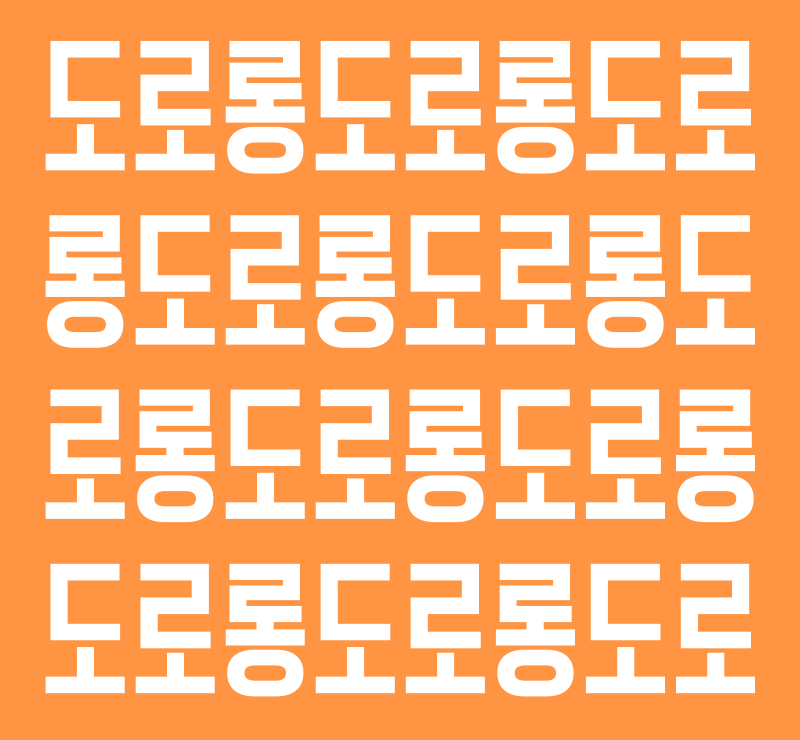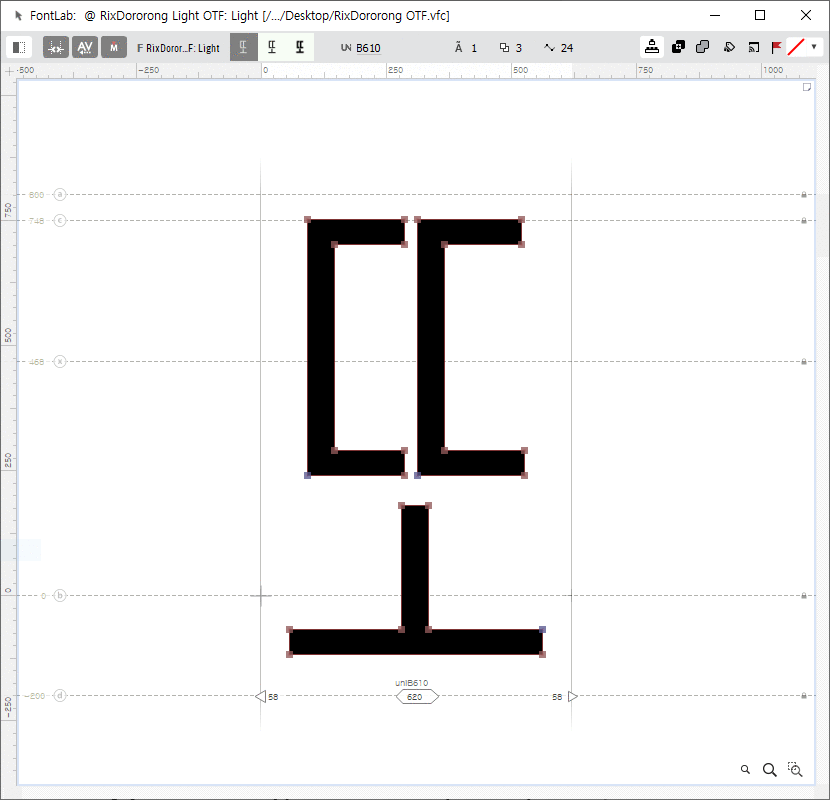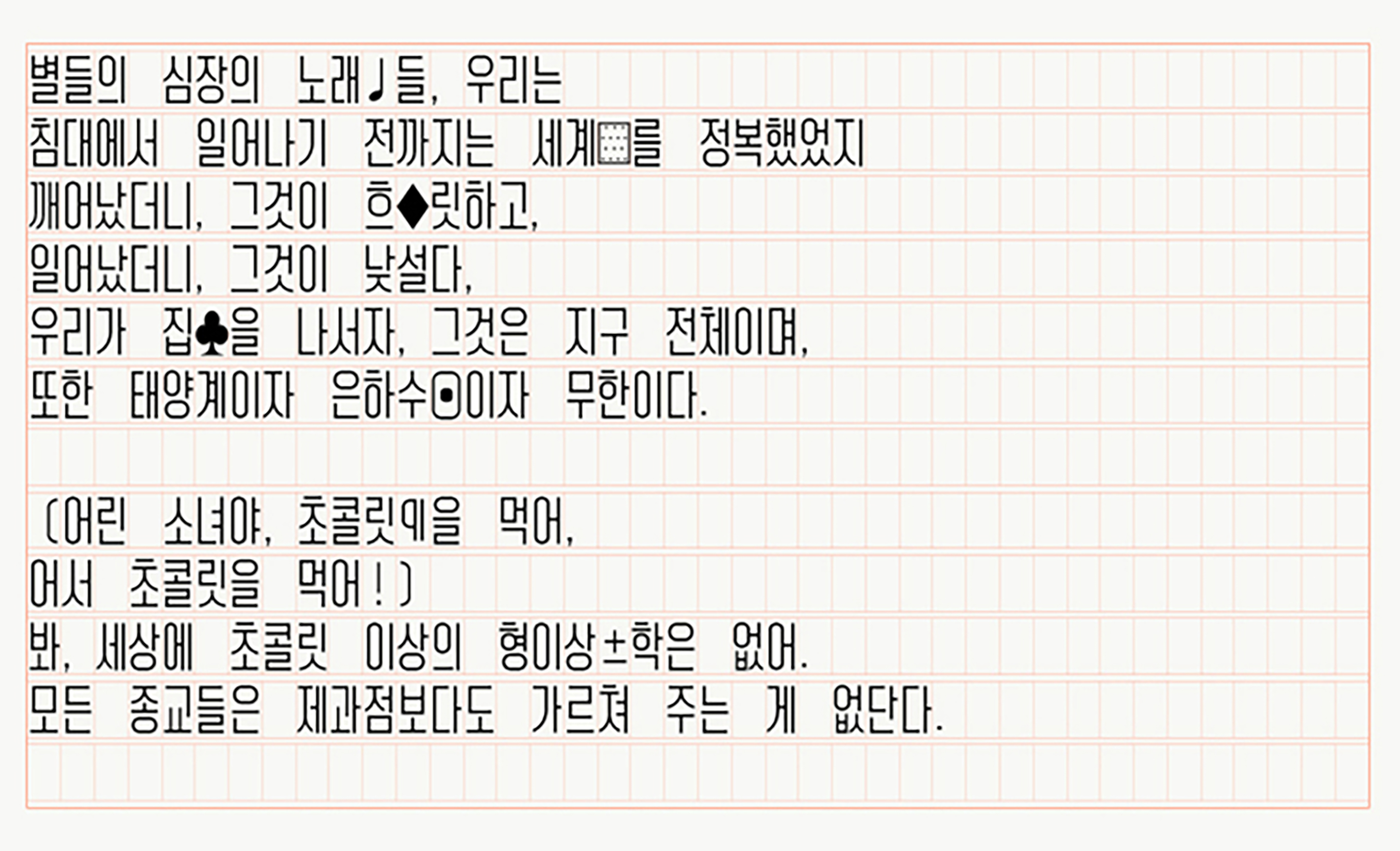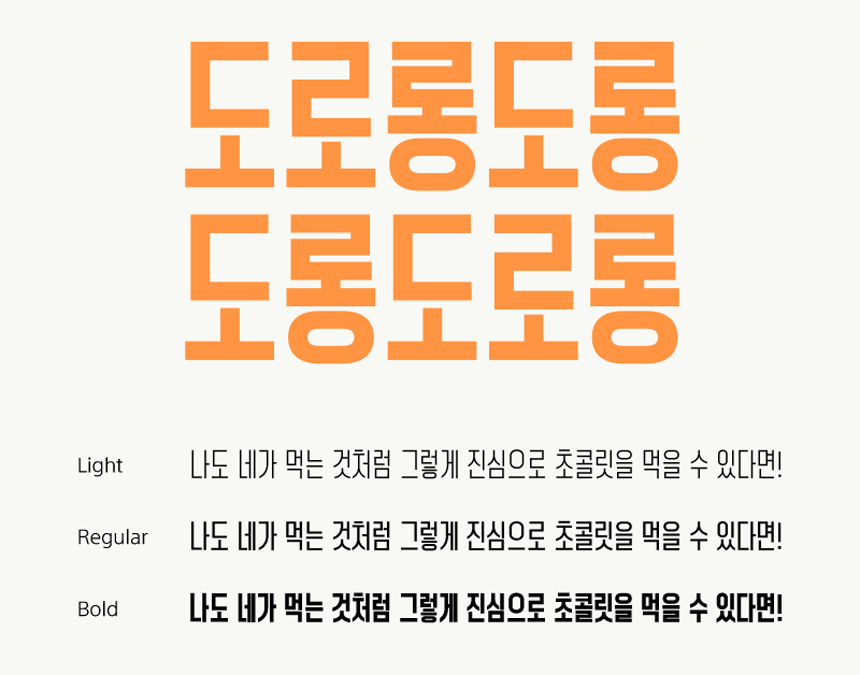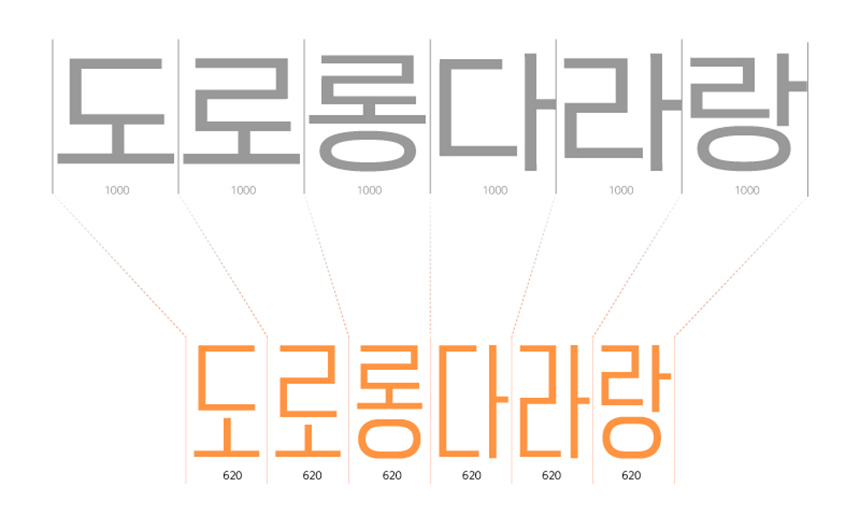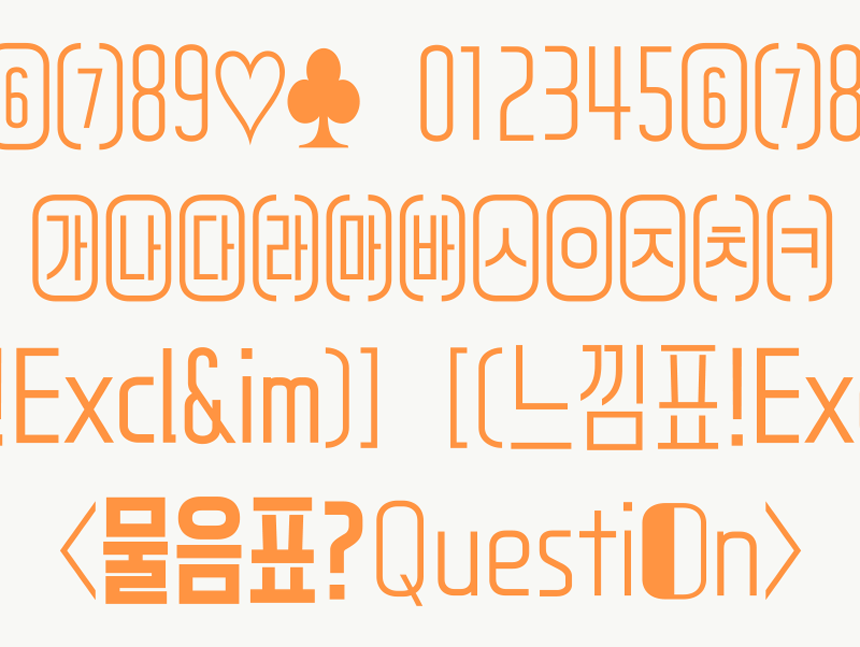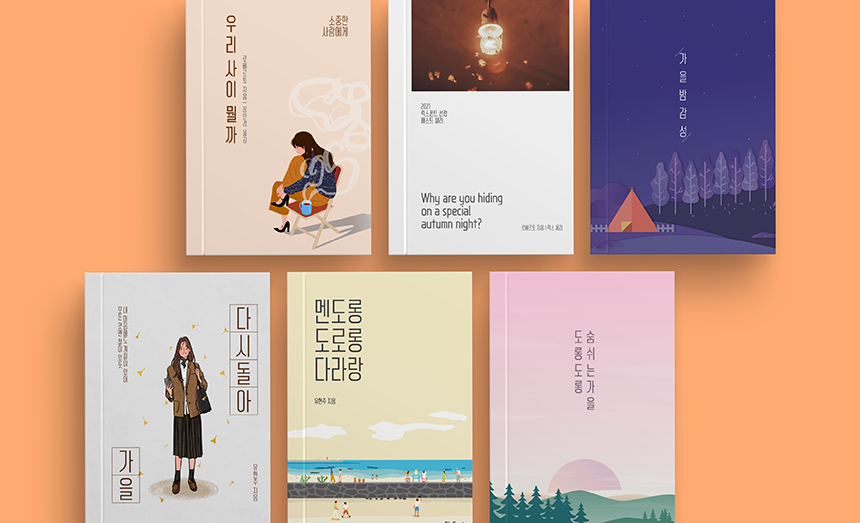
안녕하세요. 오늘은 선선한 가을과 함께 찾아온 시원한 헤드라인 폰트, 10월의 신서체「Rix도로롱」을 소개합니다! 제목용 서체이지만 얇은 거 두꺼운 거 다 되는 활용도 높은 장체 스타일의 글꼴입니다. 폰트에 대해 딥하게 알 수 있는 Rix도로롱 제작자 유현주 디자이너와의 심층 인터뷰! 먼저 함께할게요:)
안녕하세요, 유현주 디자이너님. 10월의 신서체로 처음 인사드리게 되었는데 소개 한번 부탁드릴게요!
안녕하세요. 도로롱으로 데뷔(!)하게 된 글자 만드는 것을 좋아하는 유현주입니다.
이번에 작업하신 'Rix도로롱'은 어떻게 기획하게 되신 건가요?
회사에서 최근 출시하는 폰트들이 정사각에 가까운 네모꼴인 것을 보고 장이 좁은 폰트를 그리게 되었습니다. 폭이 좁고 일정한 격자 모듈을 모티브로 길고 얇은 유리잔에 담긴 모히또가 연상되어 원제는 모히또로 정했었는데, 단어에 여름이 묻어있어서 좀 더 가벼운 느낌이 나는 도로롱으로 이름을 바꾸게 되었습니다. 이름 지어주는 게.. 글자 만드는 것만큼 어렵더라고요(웃음)
제작하면서 가장 어려웠던 부분이 있다면 무엇인지?
아무래도 좁은 자폭을 갖고 있다 보니, 획이 두꺼워지고 많아질수록 일정함을 유지하기가 어려웠어요. 그래도 이번을 기회로 글자를 그리는 다양한 방법과 규칙들을 배울 수 있었습니다:)
'Rix도로롱'의 제작자로서 이 폰트의 가장 큰 매력 포인트를 뽑는다면?
격자무늬요(편-안)ㅎㅎ 제목용으로 제작했지만 한글 자폭이 일정하기 때문에 긴 문장이나 문단을 썼을 때 보이는 격자무늬가 마음에 안정을 가져다줍니다. 직사각 형태에 꽉 찬 골격, 고정폭이 주는 깔끔하고 딱 떨어지는 매력!
디자인 영감이 필요할 때 자주 보는 디자인 플랫폼, 또는 인스피레이션(inspiration)이 있다면?
원래는 책이나 포스터의 레터링을 많이 찾아보고 모았었는데, 요즘은 기성 폰트를 제목에 사용하는 경우가 많더라고요. 그래서 요즈음엔 옛날 LP의 레터링들이나 최근에 출시되는 외국 폰트를 주로 찾아보고 있습니다.
앞으로 또 어떤 폰트를 제작하고 싶으신가요?
최근에 배리어블 폰트에 흥미가 생겨 조금씩 공부하고 있습니다. 도로롱을 만들고 나서 조금씩 변형을 해보고 있는데, 기회가 된다면 도로롱보다 더 장이 좁고 얇은 폰트에서부터 아주 넓-적하고 두꺼운 폰트까지 시리즈로 엮어보고 싶습니다:)
색다른 제목용 폰트를 원해?
글자의 폭이 넓은 정사각 꽉 찬 형태의 글꼴이 많이 나오는 추세지만, Rix도로롱은 장체 스타일의 어떻게 보면 모던하고, 또 고전적인 이미지도 가질 수 있는 특별한 서체입니다. 활용도가 높은 3가지 굵기로 파생되어 가벼운 헤드라인이나 본문에 쓰기 좋은 Light, 깔끔한 제목과 본문에 모두 사용 가능한 Regular, 그리고 눈에 띄는 타이틀/자막에도 적합한 Bold로 구성했습니다.
길쭈-욱 시원한 헤드라인
글자 폭이 좁은 Rix도로롱 폰트에서 시원~한 인상이 느껴지는 이유는 무엇일까요? 'ㄷ'이나 'ㄹ'에서 보이는 널찍한 공간감과 전체적인 디자인에 적절한 간격을 설정했기 때문입니다. 또한 모든 글자의 너비를 동일하게 설정한 고정폭 글꼴로 제작하여 깔끔하고 정돈된 인상을 줍니다. 요즘엔 글자에 따라 너비를 다르게 설정한 가변폭 글꼴이 많아 오히려 더 신선하게 다가오는 부분도 있을 것 같아요😏
뻔하지 않지만 Fun하게!
영문, 숫자, 약물의 디자인은 한글과 동일한 특징을 갖고 있어 혼용 시 조화롭습니다. 통일된 스타일이 긴 문장을 썼을 때에도 조화롭고 자연스럽게 표현됩니다. 일부 특수문자나 기호에서 재미를 느낄 수 있는 요소도 있어 더욱 다채롭게 활용할 수 있습니다.
| 이렇게 활용해 보세요
독서의 계절! 선선한 바람이 느껴지는 듯한 가을 감성 물씬 나는 북디자인 제목용 서체로 활용해 보세요. 얇은 거 두꺼운 거 다 되는 폰트로 여러 가지 스타일의 디자인 작업에 유용하고, 타이틀과 본문에 모두 사용할 수 있어요.
재밌게, 때론 귀엽게 활용해 보아요. 3종 웨이트 중 가장 두꺼운 굵기를 활용하면 눈에 잘 띄면서도 유쾌한 이미지를 주어 다양한 굿즈나 로고, 배너, 간판 등 에도 사용하기 좋습니다💟